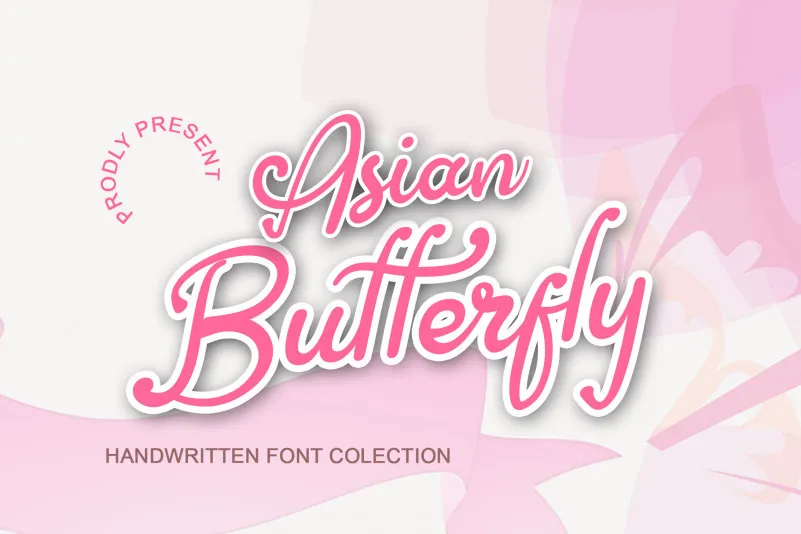
Asian Butterfly Script Font – Download Grátis
A ‘Asian Butterfly Script Font’ é uma escolha perfeita para quem busca a sofisticação tradicional do escritório oriental enquanto mantém uma sensação moderna e atual. Essencialmente, ela transmite um respeito por técnicas manuscritas ao mesmo tempo em que revela um toque contemporâneo. Com seus traços elegantes e fluidos, esta fonte é ideal para ideias criativas que vão desde os selos de correspondência até o design do título da sua marca. Suas diversas configurações facilitam a adaptação para uma ampla variedade de aplicativos, incluindo cartões de visita, aplicações digitais e materiais de escritório. Seja você um designer digital ou um criador de produtos físicos, a ‘Asian Butterfly Script Font’ atende suas necessidades, fornecendo o equilíbrio perfeito entre estética antiga e modernidade.